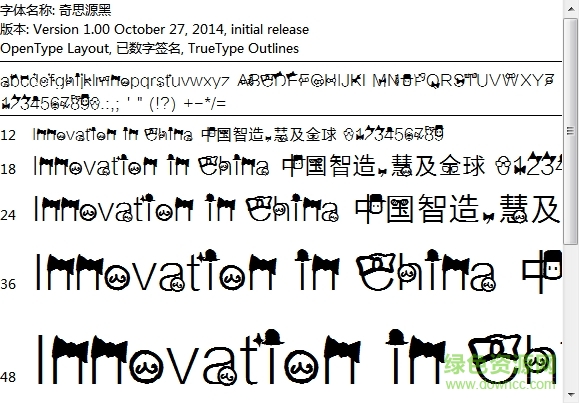
奇思源黑绅士作派体
绅士做派字体是奇思源黑推出的一款艺术字体,有着可爱的装饰点缀,给文字增添独特的趣味呈现,显得十分生动活泼起来,喜欢的朋友可以来绿色资源网收藏哦!
奇思源黑绅士作派体特色
绅士做派字体有着各种蝴蝶结、绅士帽、小胡子、四角星点缀,给文字增添了一股活泼之气,让你的设计更有青春活力的气息。